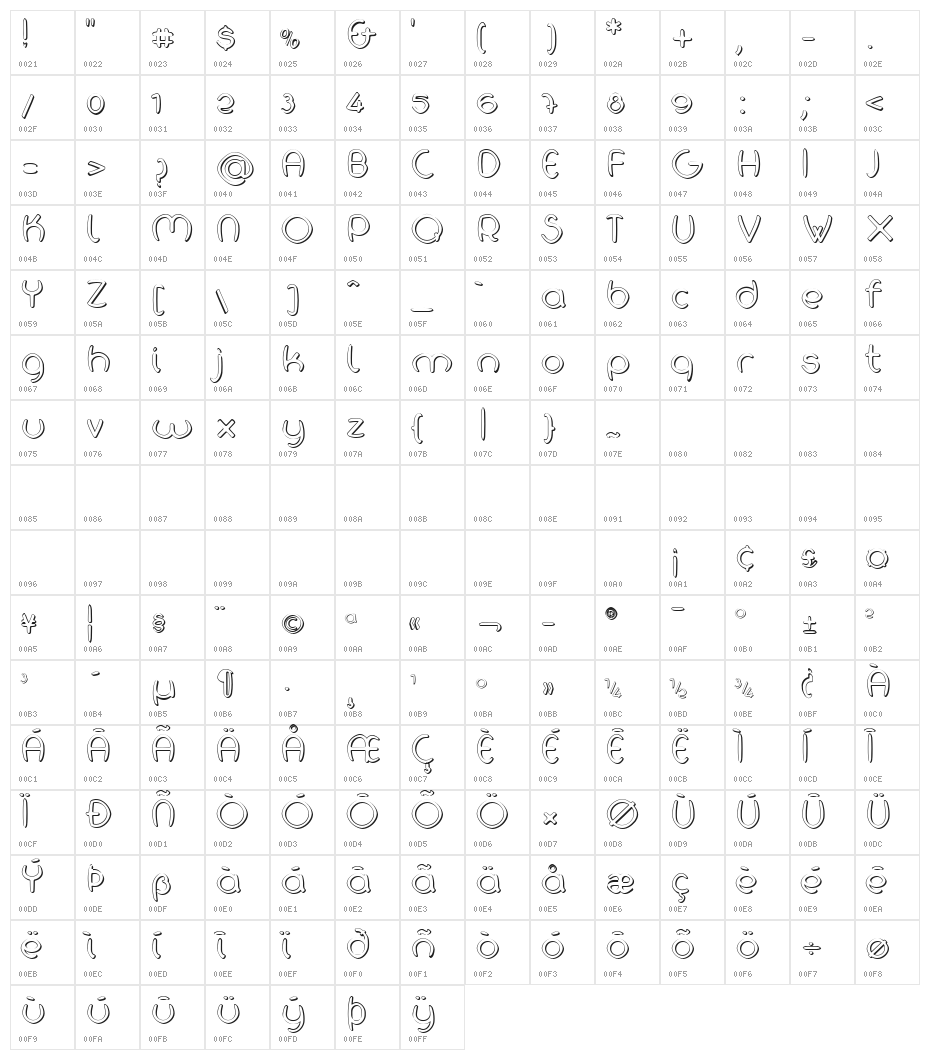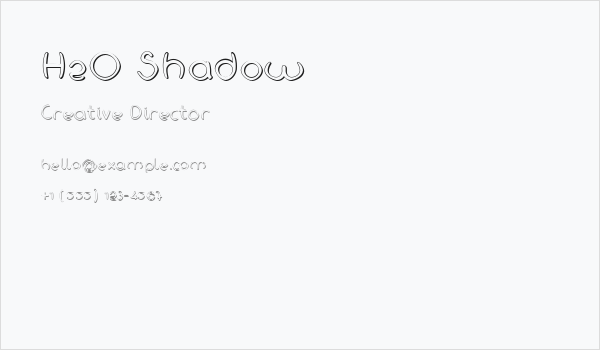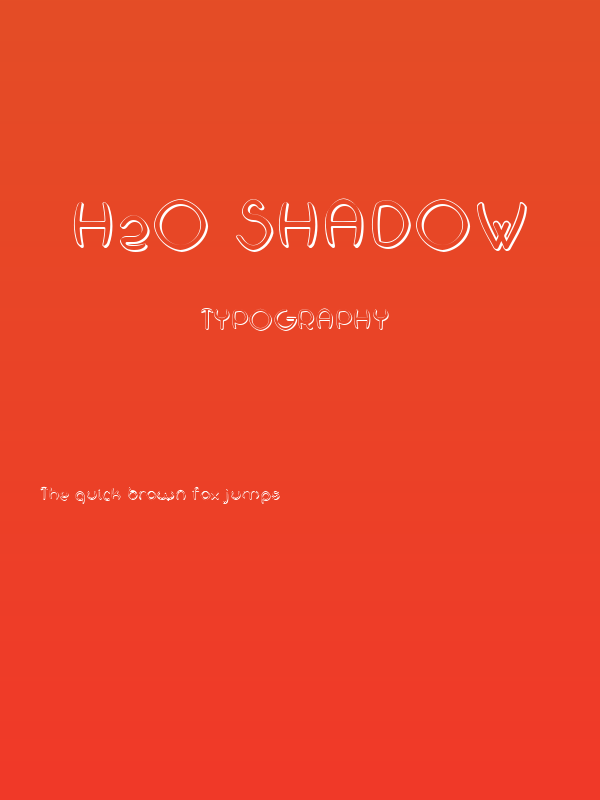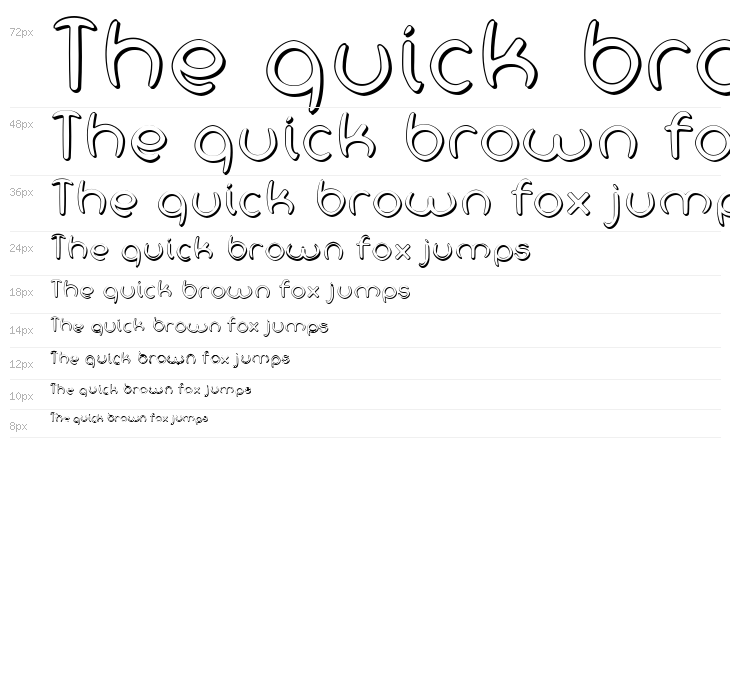
H2O Shadow Font
| Gesamtstil | Playful, Modern |
| Anwendungsfall | Headlines, Posters, Branding |
| Vorgeschlagene Projekte | Ideal for children's books, playful branding, posters, and creative projects that require a fun and engaging typeface. |